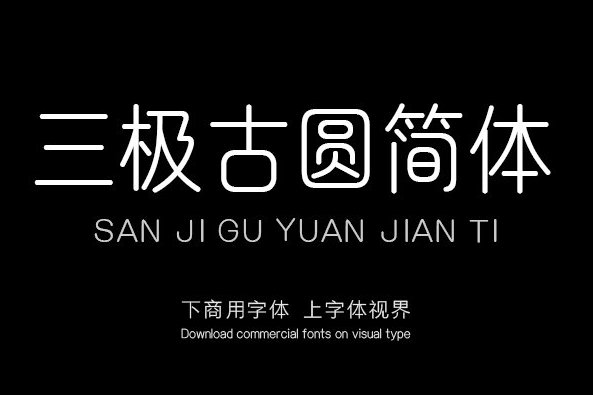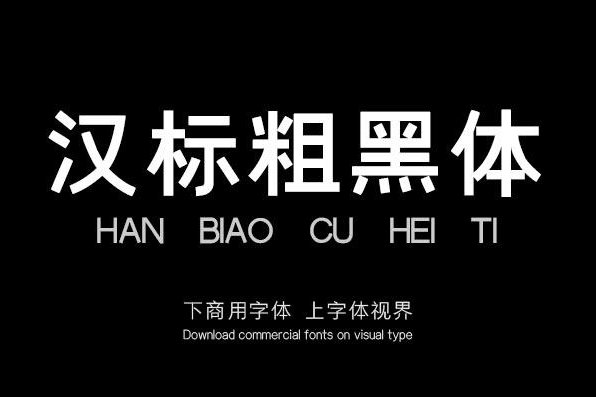
其实文字是信息传达的关键所在,不同字体渲染出的设计风格也不同,选择一个风格对应的字体让作品也会丰富多彩。小编就在这里为大家推荐几款具有代表性且高级感满满的字体吧
要说正统、端庄的字体的话,那黑体一定是要有姓名的。在商务风PPT,标题或者是用在正文中出现的频率比较高。这款汉标粗黑体笔画清朗有劲,简约美观。极具张力的曲线,加上精准的几何线条结构,在黑体的基础上增强了字体的设计感更加精致,有一种气定神闲的姿态。汉标粗黑体稳重的风格应用于信息排印与显示实为上佳选择。
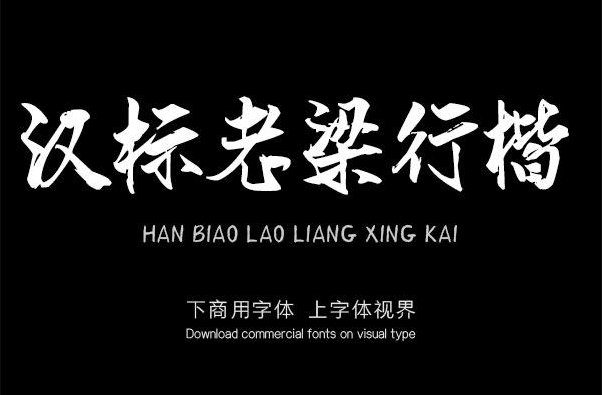
毛笔字体自带磅礴大气,浑然天成的风韵充满艺术感。常出现在PPT、影视综艺中。这款 汉标老梁行楷,延续了浓厚的书法气息,结字潇洒俊逸,运笔行云流水,气韵生动,充分体现新毛笔行书味道。使用范围更加广泛,例如文艺类的书刊、品牌广告和产品包装设计,以及社交网络的个性化用字都相得益彰。
三极古圆简体,具有古法圆通、朴拙之感,字形融合了象形、篆书等古朴字形,风格简洁明快,独具一格。字体轻巧简洁,古拙而不凡。粗细匀称,起笔收笔为圆头,折、钩、撇捺转折圆润饱满,具有古拙婉转的气质。视觉效果简洁易识别,实用性很高。以上字体有您喜欢的可以保存图片,图片识别字体 。在我们字体视界的官网上下载您喜欢的字体,字体视界支持免费字体下载试用,如果需要商用还可以联系购买商用字体授权哦~